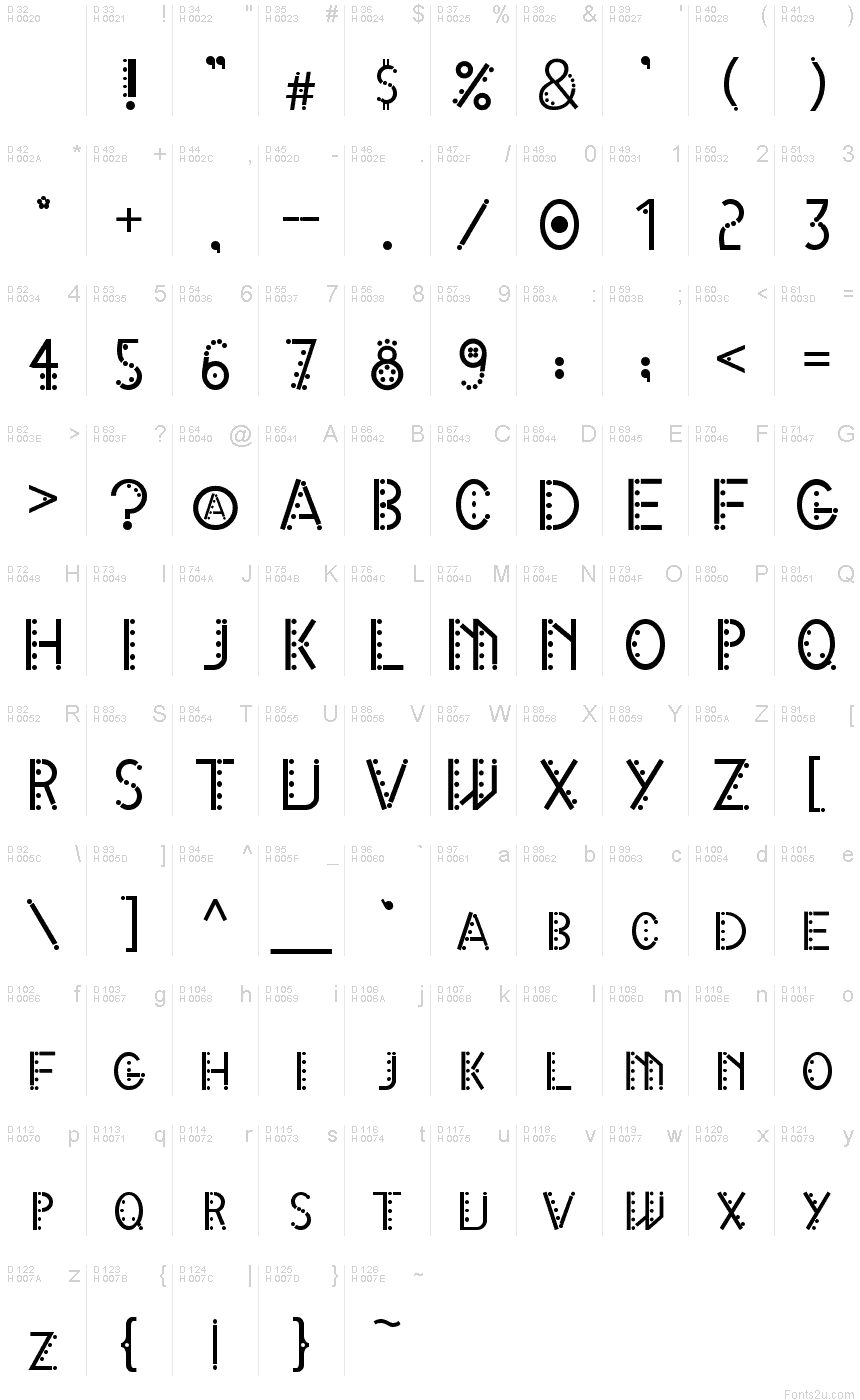
Krój Lyman autorstwa Tres Seymour to darmowa, dekoracyjna czcionka typu display. Wyróżniają ją kanciaste kształty liter, otwarte prześwity i rytmiczne kropki biegnące przez każdy znak. Powtarzające się koliste elementy nadają jej wzorzysty, ręcznie wykonany charakter, nie zatracając przy tym czytelności podstawowej struktury liter.
Lyman to darmowy font, który świetnie sprawdza się w tytułach na plakatach, ulotkach, okładkach albumów, logotypach i dekoracyjnych zaproszeniach. Dzięki wycinanym liniom i akcentom w formie kropek tworzy silny graficzny wzór, który przyciąga wzrok. Doskonale nadaje się również do tworzenia szyldów, opakowań i krótkich tekstów, w których sama liternicza forma ma stanowić główny element projektu.